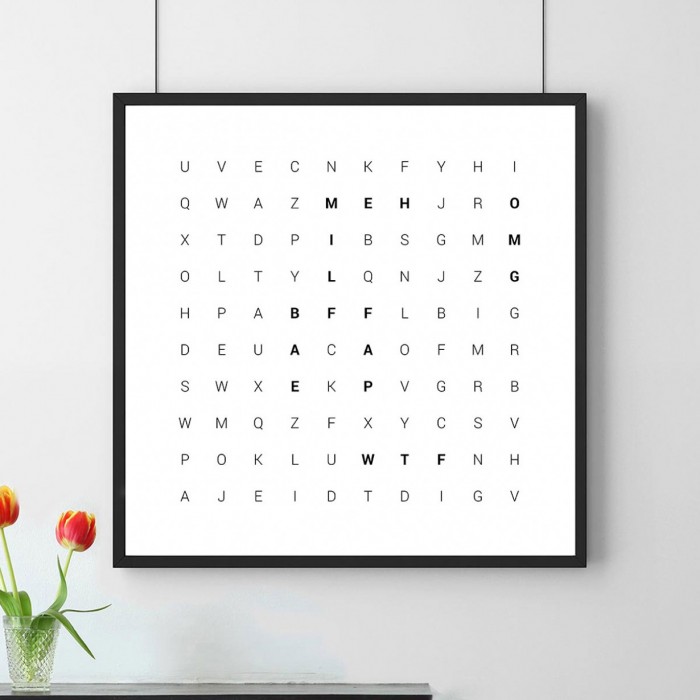
Schrift für Geschenkidee gesucht
Ganz spontan: Da würde mit eine Monospace besser gefallen, die gäbe ein ruhigeres Gesamtbild.
Beispielsweise
oder irgendwas in der Richtung.
Aber die Tulpen sind hübsch ;-)